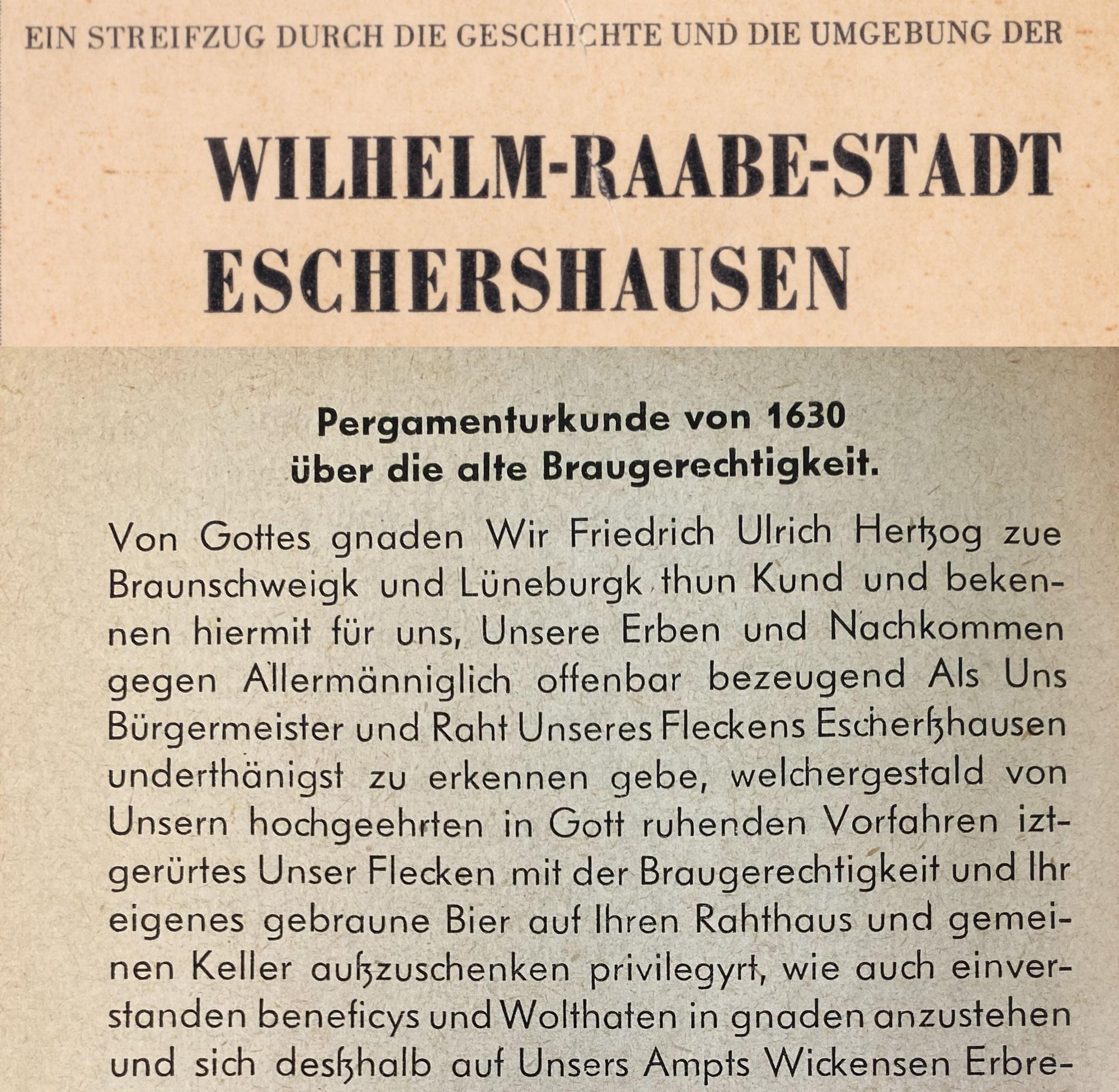
Schriften aus einem Buch von 1957 (Ein Streifzug durch die Geschichte und die Umgebung der Stadt Eschershausen)
Ich glaube, die Schriftart des Fließtextes ist die Erbar-Grotesk. Stimmt das?
Was ist die Schrift/sind die Schriftarten der Titelseite?
Es handelt sich hier um ein Büchlein im B6-Format, das von einer schon lange nicht mehr bestehenden Ein-Mann-Druckerei  (C. Bruns oHG., Eschershausen) gedruckt wurde. Eine ISBN-Nummer gibt es nicht, und selbst das Erscheinungsjahr kann nur ungefähr geschätzt werden, ist aber wahrscheinlich 1957. Der Titel ist, wie im Bild angegeben, „Ein Streifzug durch die Geschichte und die Umgebung der Stadt Eschershausen“. Autor ist Adolf Lucé. Sonst gibt es zu dieser Veröffentlichung keine mir bekannten  Informationen.
WILHELM … ist aus einer Bodoni gesetzt.
EIN STREIFZUG … ist ebenfalls aus einer Bodoni gesetzt, das G findet man heute u.a. bei einer Bodoni Six oder Twelve.
Welche Bodoni-Schnitte das genau waren und wie die damals in Blei hießen, kann ich dir aber nicht sagen.
Mit der Erbar Grotesk für den Fließtext liegst du völlig richtig.